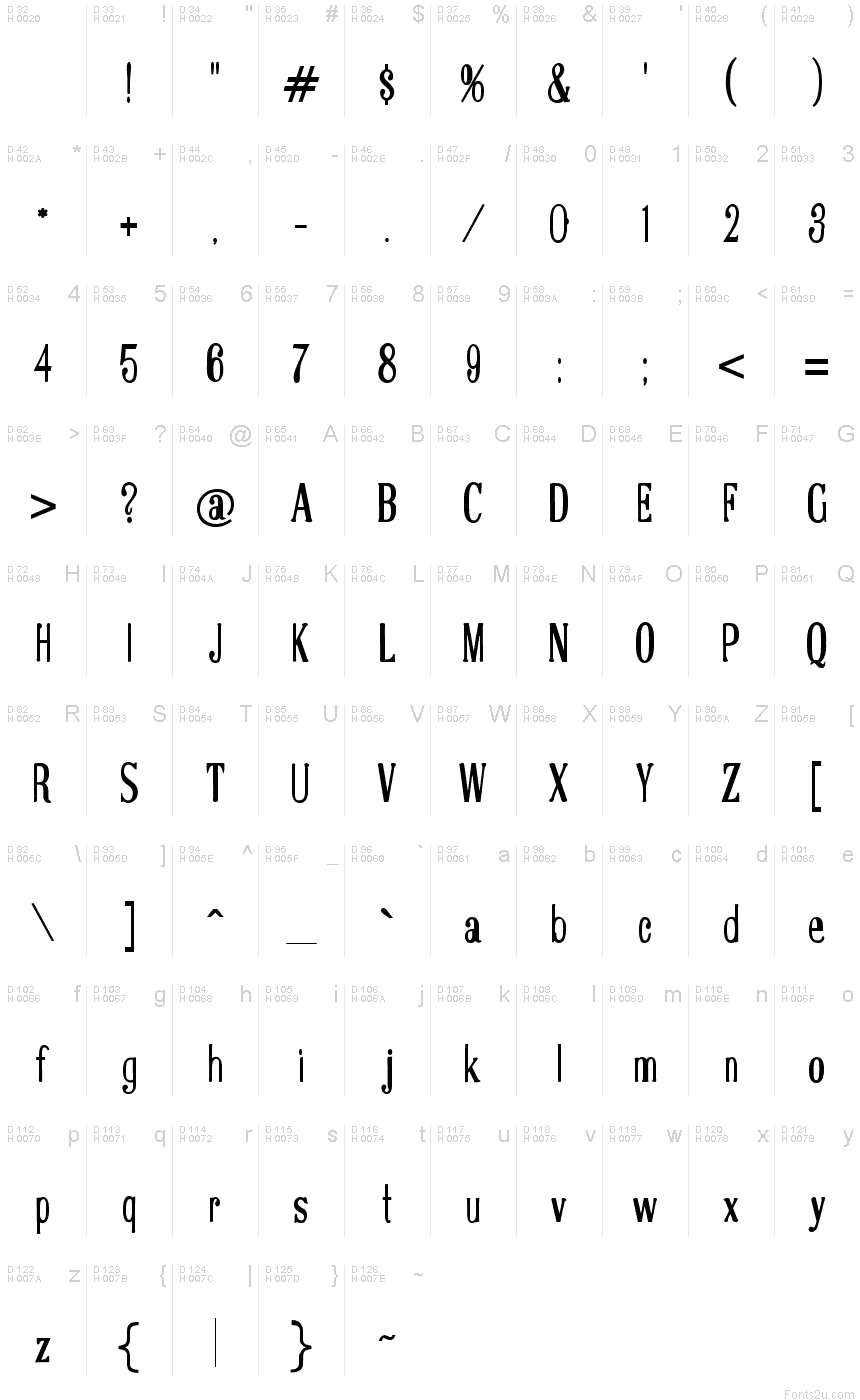
Scoglietto di CybaPeeCreations è un carattere serif gratuito in stile art nouveau del 1999, con lettere alte e strette, piedi ricurvi e un fascino fiabesco. Il design punta su un forte contrasto e curve morbide, mentre dettagli come le grazie a uncino e le sommità affusolate conferiscono al carattere un tocco decorativo, quasi disegnato a mano.
Si adatta perfettamente al branding di boutique, menu di caffè, copertine di libri, titoli di poster e packaging, dove un tocco di fascino d'altri tempi aiuta a valorizzare il messaggio. Essendo un font gratuito, Scoglietto dà il meglio di sé in titoli brevi, loghi e intestazioni, perché le sue forme allungate e i riccioli giocosi hanno bisogno di spazio per esprimere il loro carattere.